落ち着いた印象で高級感のあるフォントです。全て大文字の英語フォントです。
ウエイトは6種類です。
Gowun Batang
癖がなく落ち着いた印象のセリフ書体です。
ウエイトは2種類です。
Sarpanch
癖がなく落ち着いた印象のセリフ書体です。
ウエイトは6種類です。
Marcellus SC
Quicksand
ウエイトは6種類です。
Homenaje
おしゃれ!英語フリーフォント
無料で使えるおしゃれな英語フォントを紹介します。
MOON
Kilowatt
Cornerstone
Phenomena
ウエイトは7種類です。
Pixer
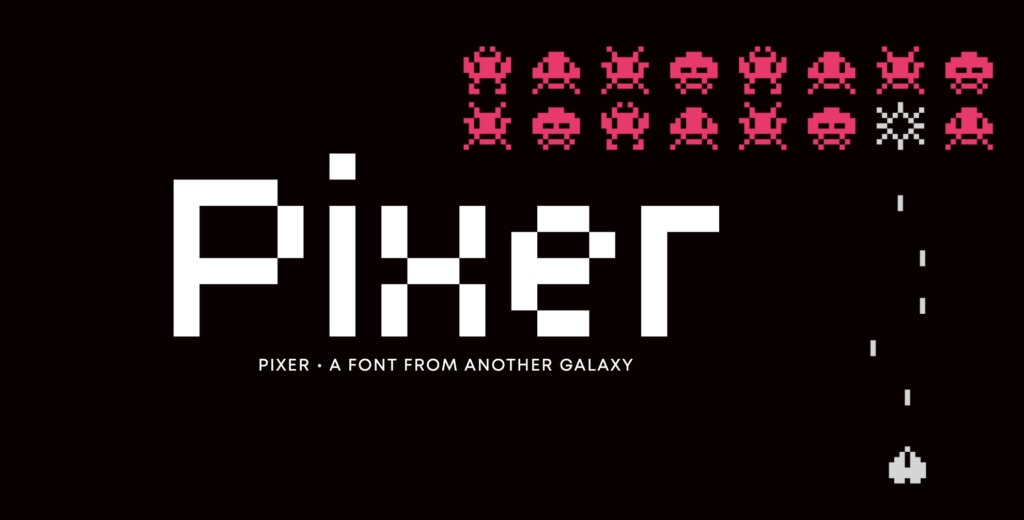
Helvetica
Bebas Neue
まとめ
おしゃれな筆記体のフォントの紹介でした。